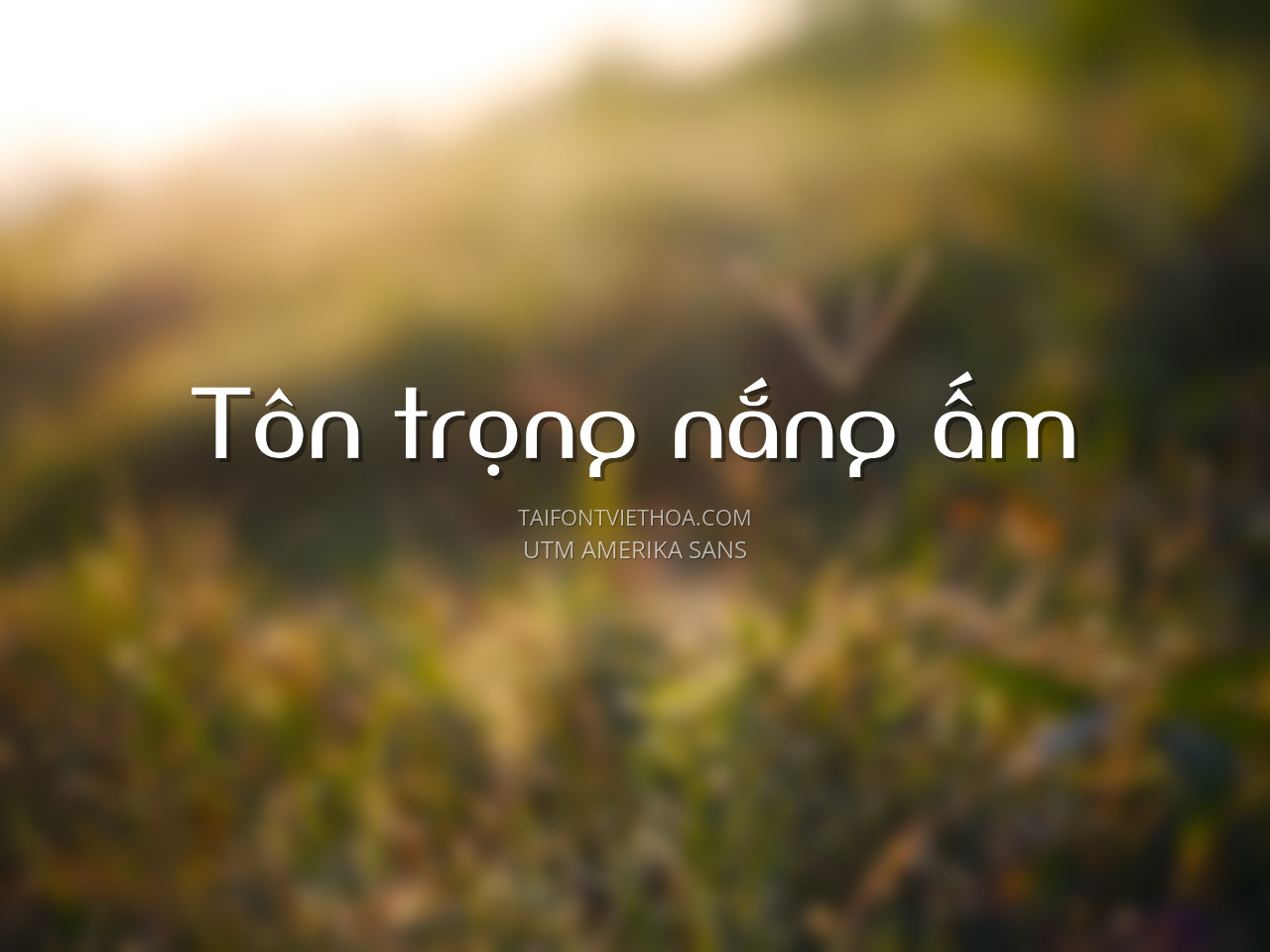
Font việt hóa UTM Amerika Sans
Giới thiệu về font UTM Amerika Sans
UTM Amerika Sans là phiên bản Việt hóa của font Amerika Sans – một kiểu chữ sans-serif hiện đại, linh hoạt và dễ đọc. Font gốc được thiết kế bởi nhà thiết kế nổi tiếng tại Mỹ, lấy cảm hứng từ phong cách typography tối giản và tinh tế. Phiên bản Việt hóa đã được hoàn thiện để hỗ trợ đầy đủ tiếng Việt và hơn 200 ngôn ngữ khác, giúp mở rộng khả năng ứng dụng trong các dự án thiết kế đa dạng.
Đặc điểm thiết kế và ứng dụng của UTM Amerika Sans
UTM Amerika Sans sở hữu cấu trúc sans-serif không chân với các nét chữ vuông vức, mềm mại và cân đối. Font có thiết kế tối giản, dễ đọc và linh hoạt, phù hợp với nhiều kích thước và môi trường hiển thị khác nhau. Các ký tự được cân chỉnh kỹ lưỡng để đảm bảo sự hài hòa và cân bằng trong bố cục thiết kế.
Font được ứng dụng rộng rãi trong thiết kế logo, nhận diện thương hiệu, quảng cáo, bao bì sản phẩm và các dự án truyền thông đa phương tiện. Các ngành nghề phù hợp gồm: công nghệ, quảng cáo, thời trang, truyền thông, giáo dục và startup.